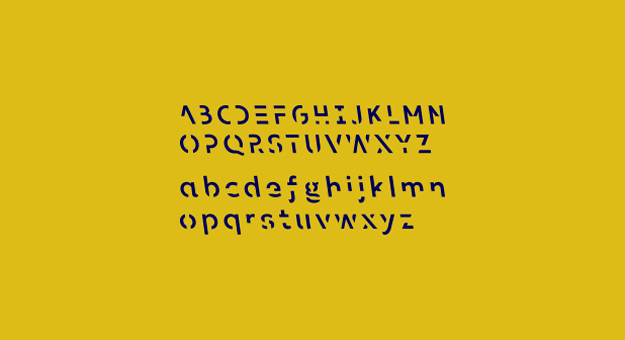
Дизайнеры придумали шрифт, развивающий память
С говорящим названием Sans Forgetica
Исследователи Мельбурнского университета использовали законы дизайна и психологии, чтобы создать шрифт, помогающий запомнить прочитанное.
Название шрифта Sans Forgetica состоит из имен двух классических — Comic Sans и Helvetica. В новом шрифте буквы наклонены влево под углом в 7 градусов и в каждом символе имеются выемки.
Чтобы помочь читателю запомнить написанное, дизайнеры использовали психологический феномен «целесообразной трудности» (desirable difficulty). Этот термин ввели в 1994 году ученые Элизабет и Роберт Бйорк для описания препятствий, которые обеспечивают лучшее запоминание ценой первоначального торможения прогресса. Таким образом, задумываясь над незнакомыми силуэтами букв Sans Forgetica, читатель получает больше времени, чтобы сосредоточиться на написанном и лучше это усвоить.